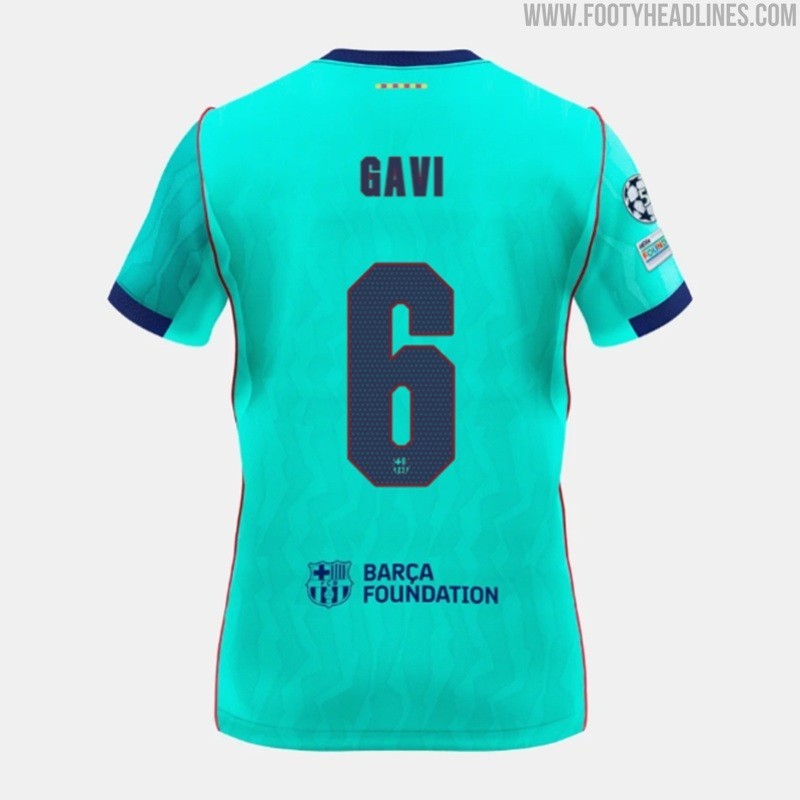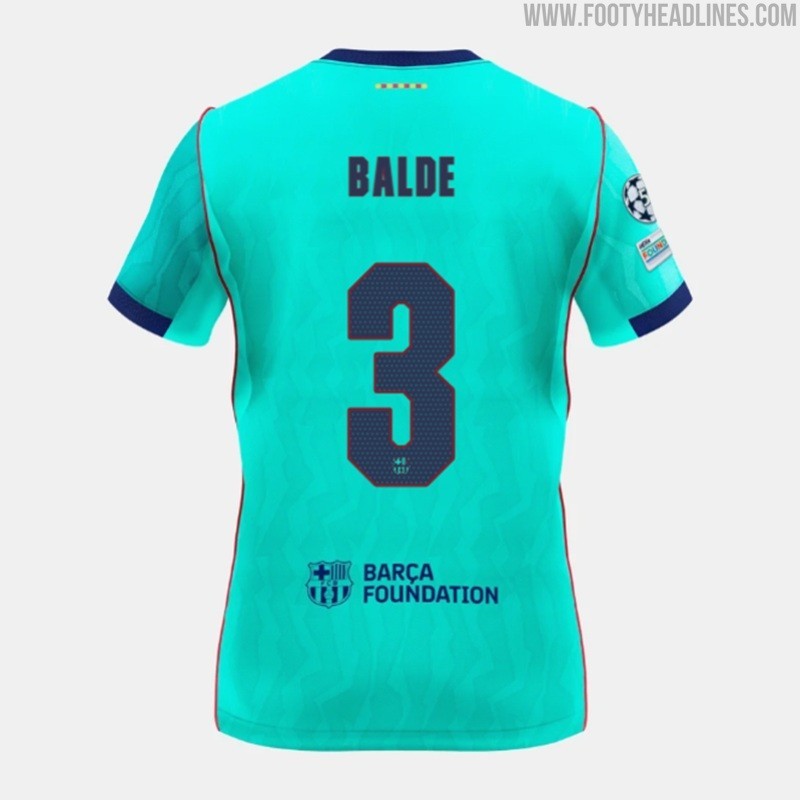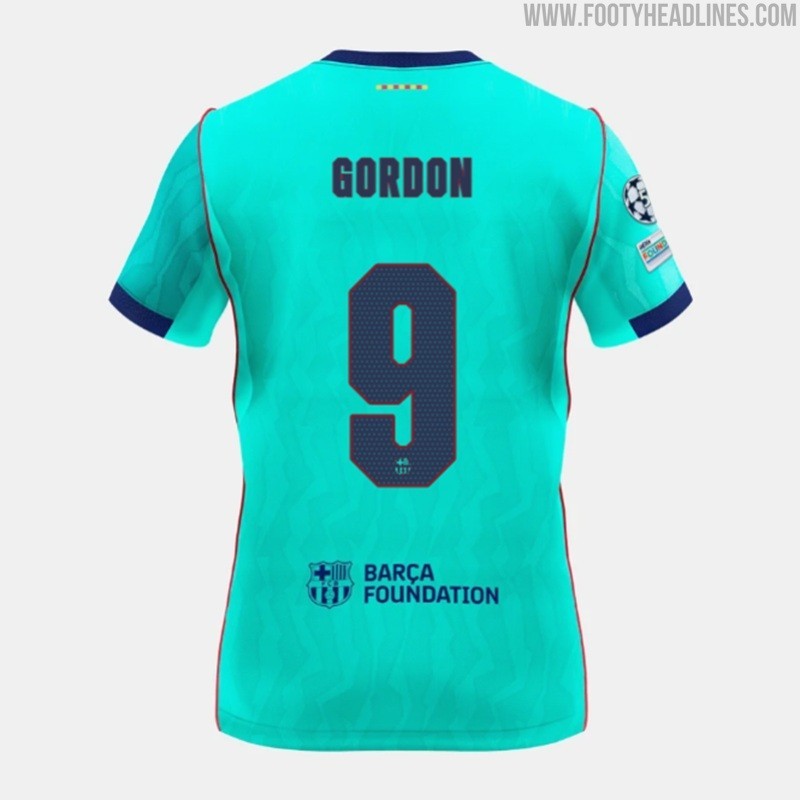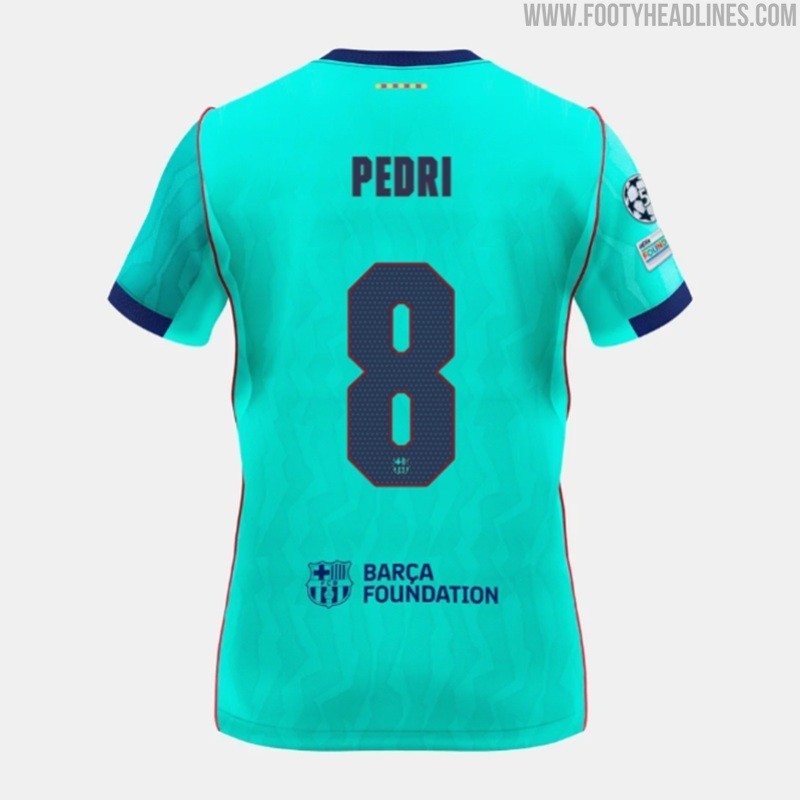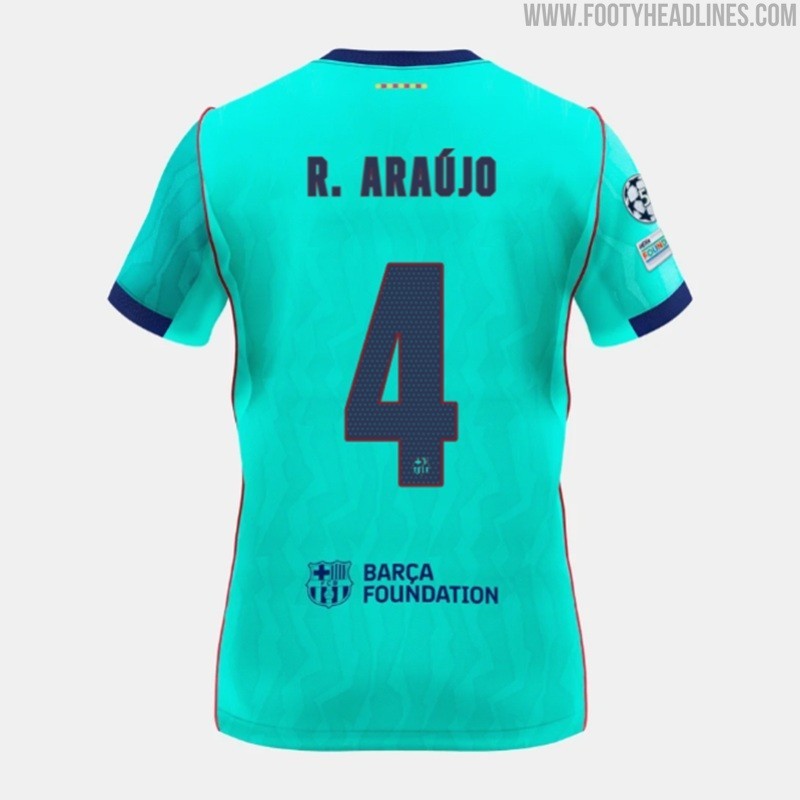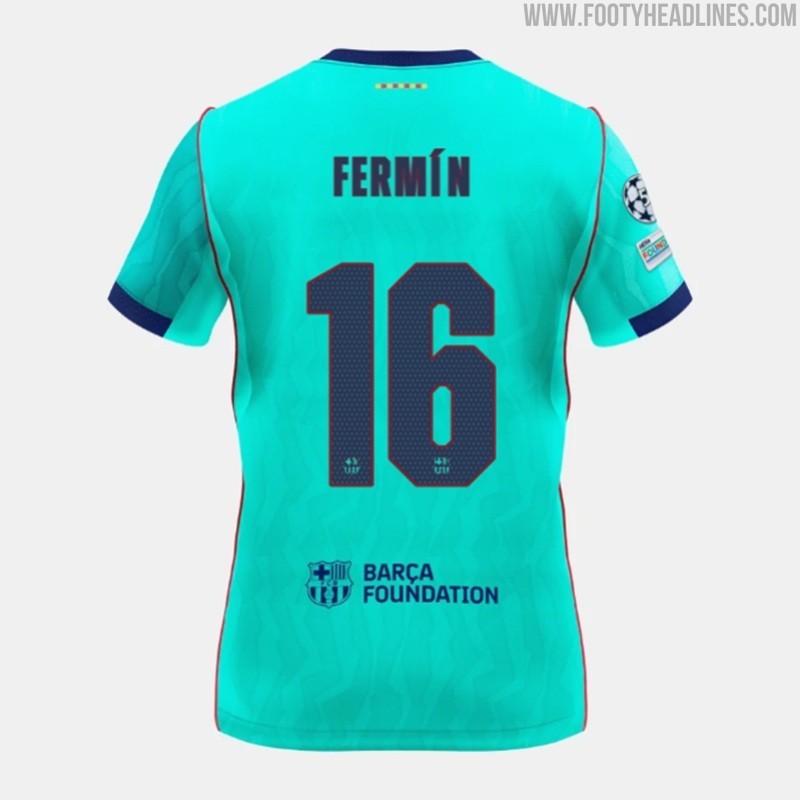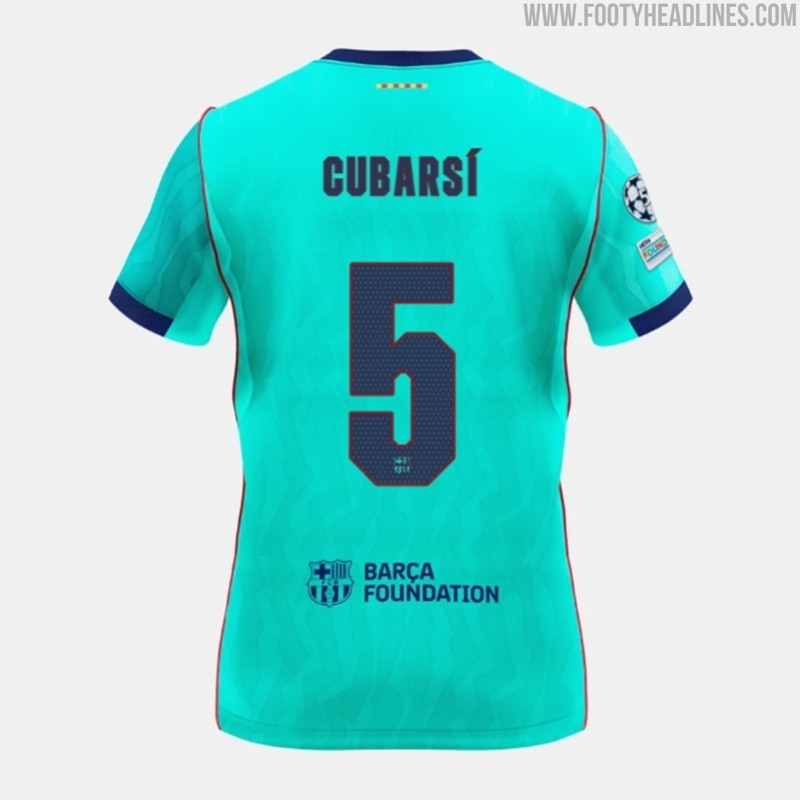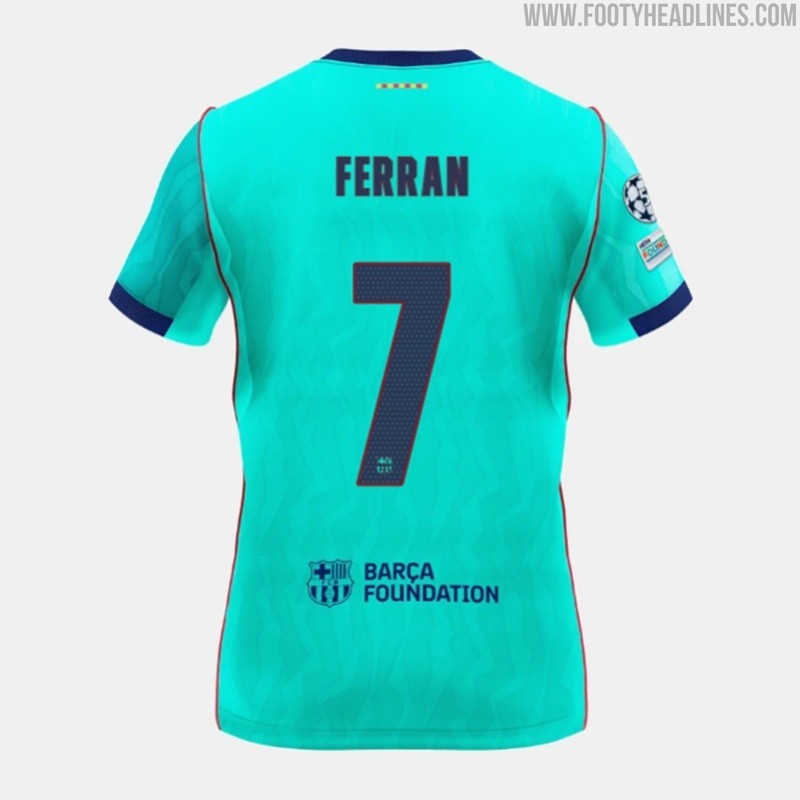
Se presenta la nueva tipografía de la tercera camiseta del FC Barcelona para la temporada 26-27
• Presentación Oficial: El FC Barcelona ha lanzado una nueva tipografía personalizada y exclusiva para su tercera camiseta de la temporada 2026-2027.
• Características de Diseño: La nueva tipografía presenta una estética moderna, estructurada, cuadrada y angular, diferenciándose de los diseños más suaves de las camisetas local y visitante.
Tras el lanzamiento oficial de su nueva tercera camiseta, el FC Barcelona ha presentado una tipografía totalmente nueva y personalizada, diseñada en exclusiva para la tercera camiseta de la temporada 2026-2027.
Tipografía de la tercera camiseta del FC Barcelona 26-27
Echa un vistazo a la nueva tipografía de la tercera camiseta del FC Barcelona 26-27 aquí abajo.
La nueva tipografía de la tercera camiseta del FC Barcelona 26-27 presenta una estética claramente moderna y estructurada que la distingue del resto de la colección del club para la temporada 2026-2027.
A diferencia de la tipografía más suave, redondeada y estilizada que lucen las camisetas locales y visitantes del Barcelona para la temporada 2026-2027, la tipografía de la tercera camiseta tiene un diseño mucho más cuadrado, bloqueado y angular. Los bordes marcados y las proporciones cuadradas dan a los nombres y números de los jugadores un aspecto limpio y de alta tecnología en la espalda de la camiseta de color turquesa brillante.
En azul marino oscuro, los números y las letras ofrecen el máximo contraste con el vibrante color de fondo para una visibilidad óptima en el campo.
Tipografías del FC Barcelona 26-27